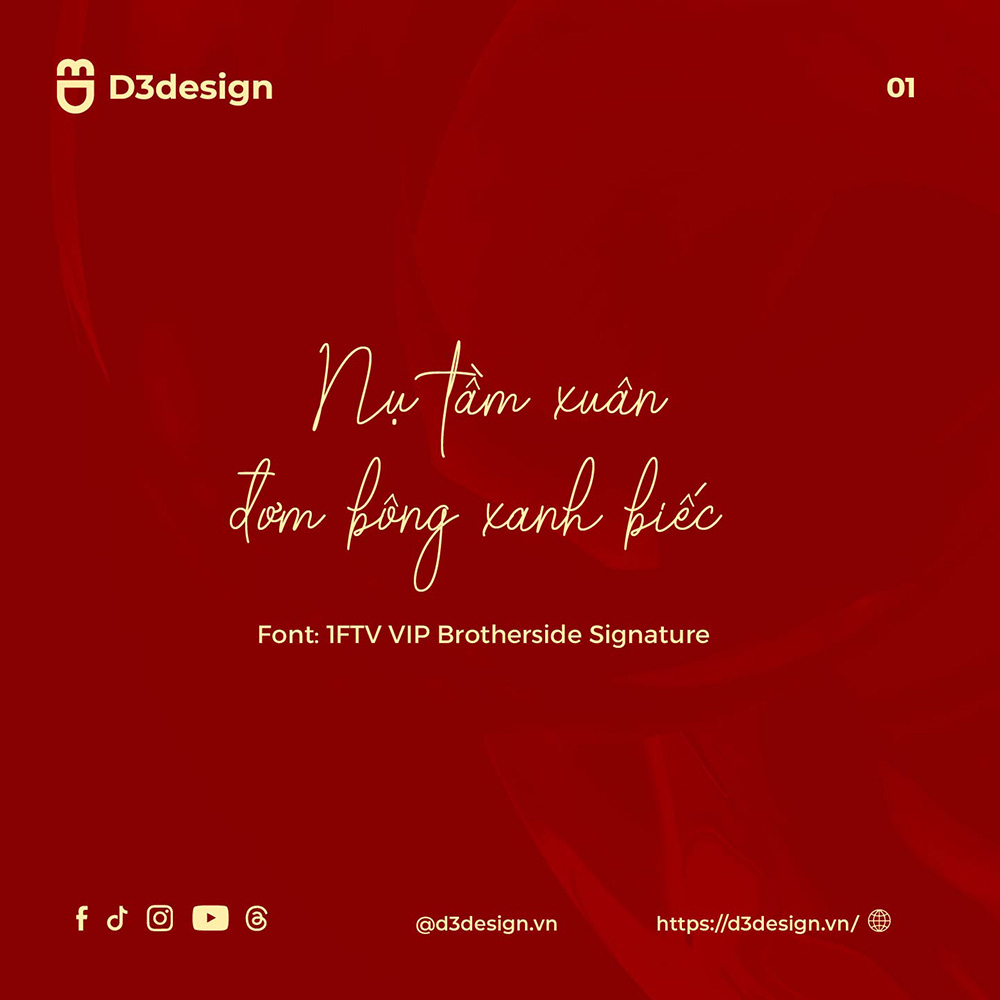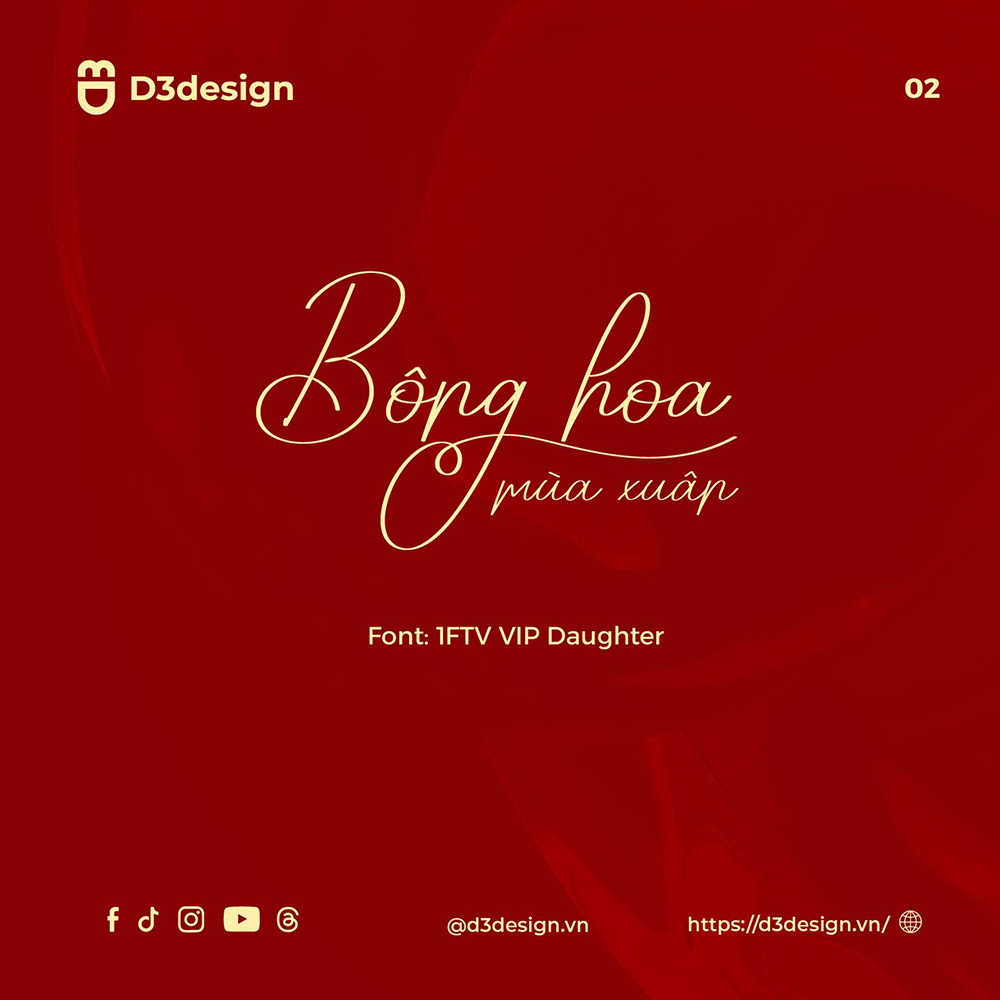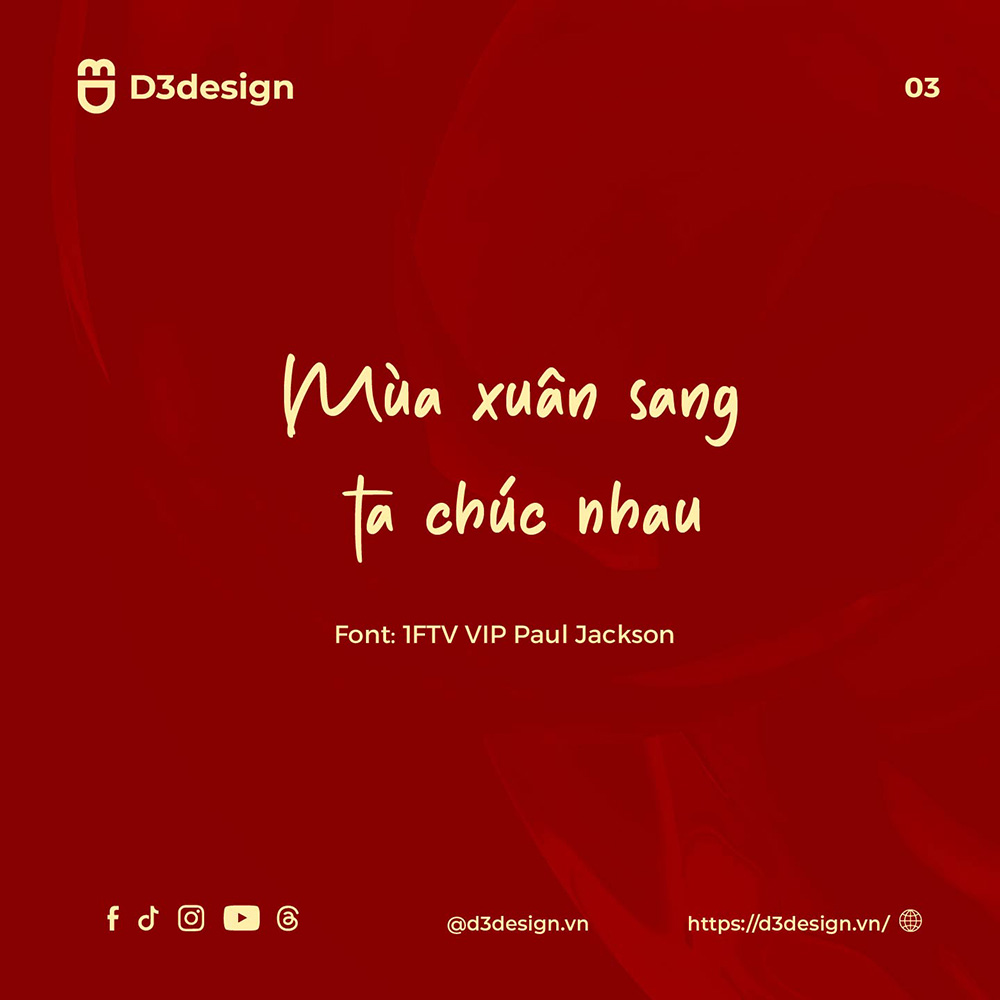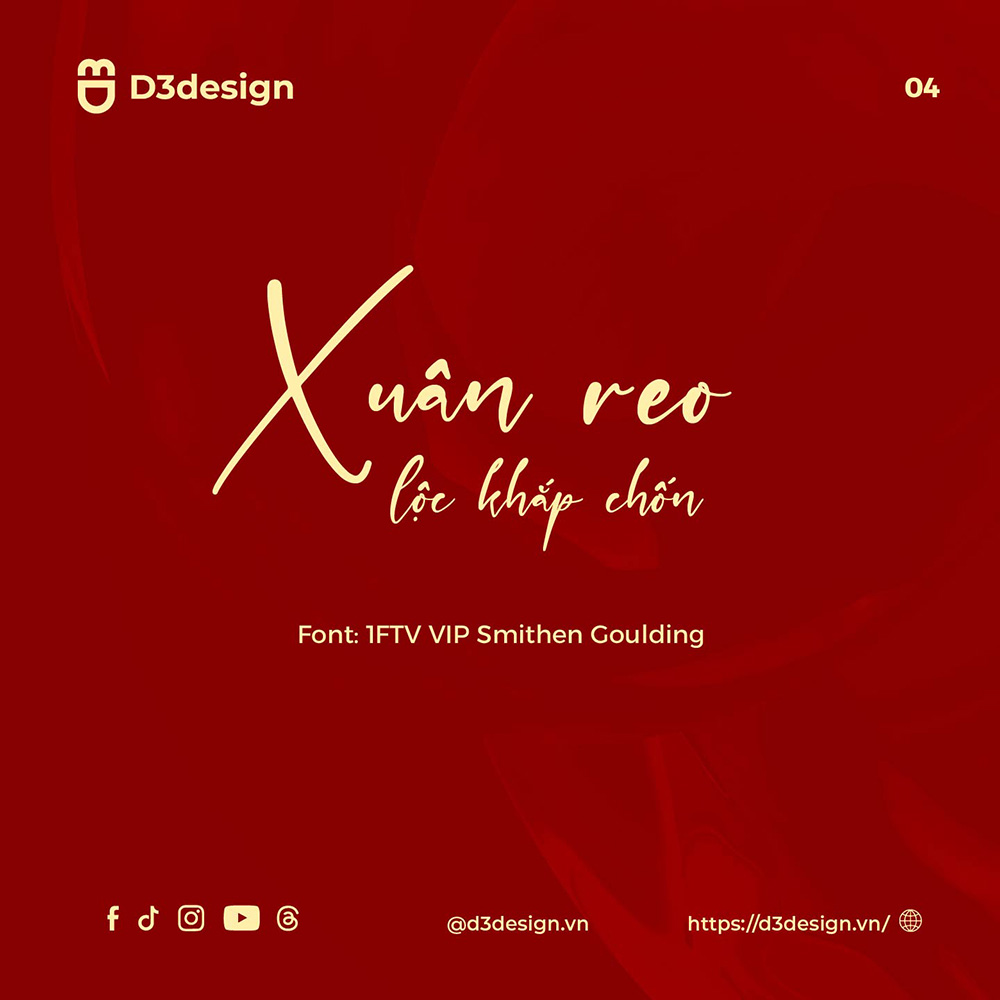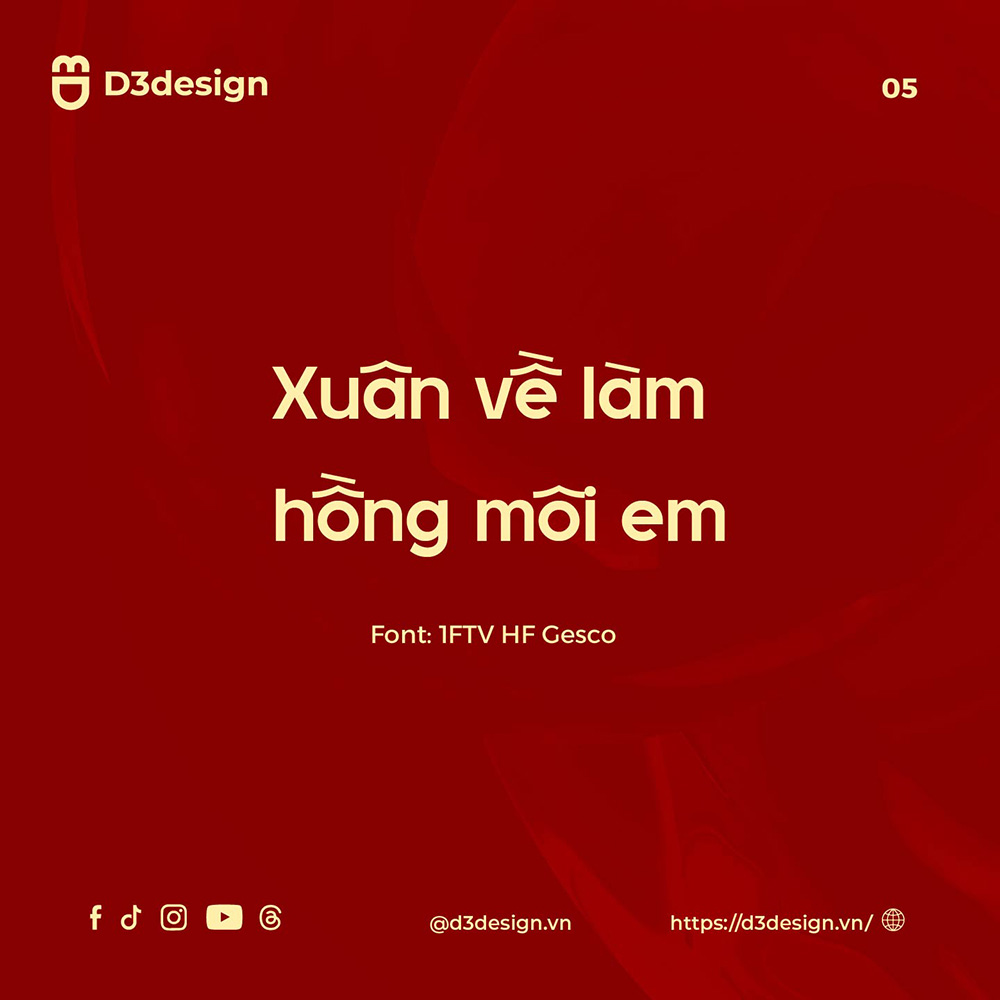
Tải Font Chữ Việt Hóa Dành Cho Tết Nguyên Đán 2026
Tết Nguyên Đán 2026 đang đến gần, nhu cầu thiết kế banner, poster, thiệp chúc Tết, bao lì xì, ấn phẩm truyền thông ngày càng tăng cao. Một trong những yếu tố quan trọng nhất quyết định chất lượng thiết kế Tết chính là font chữ Việt hóa – vừa đẹp, vừa thể hiện đúng tinh thần ngày Xuân.
Bài viết dưới đây sẽ giúp bạn chọn đúng font chữ Việt hóa dành cho Tết Nguyên Đán 2026, đồng thời gợi ý những kiểu font đang được ưa chuộng nhất hiện nay.
1. Vì sao nên dùng font chữ Việt hóa cho Tết Nguyên Đán 2026?
Font chữ Việt hóa là những font đã được chỉnh sửa để hiển thị đầy đủ dấu tiếng Việt, tránh lỗi font khi thiết kế hoặc in ấn. Đặc biệt với Tết Nguyên Đán, việc dùng font Việt hóa mang lại nhiều lợi ích:
Hiển thị chuẩn dấu tiếng Việt, không lỗi ký tự
Dễ sử dụng trên mọi phần mềm thiết kế (Photoshop, Illustrator, Canva, Corel…)
Truyền tải đúng tinh thần truyền thống – may mắn – sum vầy
Tăng tính chuyên nghiệp cho ấn phẩm Tết
👉 Với Tết Nguyên Đán 2026, xu hướng thiết kế đang quay lại giá trị truyền thống kết hợp hiện đại, nên font chữ đóng vai trò cực kỳ quan trọng.
2. Các kiểu font chữ Việt hóa phù hợp cho Tết Nguyên Đán 2026
Font chữ thư pháp Việt hóa – Linh hồn của thiết kế Tết
Font thư pháp luôn là lựa chọn hàng đầu cho thiết kế Tết Nguyên Đán.
Phù hợp cho:
Câu đối Tết
Thiệp chúc Xuân
Banner chúc mừng năm mới
Poster sự kiện Tết
Đặc điểm:
Nét chữ mềm mại, bay bổng
Mang đậm nét văn hóa Á Đông
Gợi cảm giác may mắn, tài lộc, an khang
Font chữ viết tay Việt hóa – Gần gũi và ấm áp
Font chữ viết tay Việt hóa tạo cảm giác thân thiện, tự nhiên, rất phù hợp với không khí gia đình ngày Tết.
Phù hợp cho:
Thiệp chúc Tết cá nhân
Lì xì Tết
Bài đăng mạng xã hội Tết 2026
Ưu điểm:
Dễ đọc
Trẻ trung, hiện đại
Phù hợp cả thiết kế truyền thống lẫn sáng tạo mới
Font chữ đậm, bo tròn – Xu hướng thiết kế Tết hiện đại 2026
Trong Tết Nguyên Đán 2026, nhiều thương hiệu ưa chuộng font chữ đậm – tròn – chắc, thể hiện sự sung túc, đủ đầy.
Phù hợp cho:
Banner quảng cáo Tết
Poster khuyến mãi
Bao bì sản phẩm dịp Tết
Đặc điểm nổi bật:
Dễ gây chú ý
Thể hiện sự vững vàng, phát triển
Rất hợp với màu đỏ, vàng, cam – màu chủ đạo của Tết
Tiêu chí chọn font chữ Việt hóa cho Tết Nguyên Đán 2026
Khi lựa chọn font chữ Tết, bạn nên lưu ý:
✅ Có đầy đủ dấu tiếng Việt
✅ Dễ đọc, không quá rối
✅ Phù hợp tinh thần Tết (truyền thống – may mắn – sum vầy)
✅ Có thể dùng cho cả in ấn và online
✅ Không lỗi font khi xuất file
Ứng dụng font chữ Việt hóa trong thiết kế Tết 2026
Font chữ Việt hóa Tết Nguyên Đán 2026 được sử dụng rộng rãi trong:
Thiết kế banner Tết
Poster, standee, backdrop sự kiện Xuân
Thiệp chúc Tết doanh nghiệp & cá nhân
Bao lì xì, lịch Tết
Bài đăng Facebook, Zalo, Instagram dịp Tết
Một font chữ phù hợp sẽ giúp nâng tầm toàn bộ thiết kế, tạo ấn tượng mạnh mẽ ngay từ cái nhìn đầu tiên.